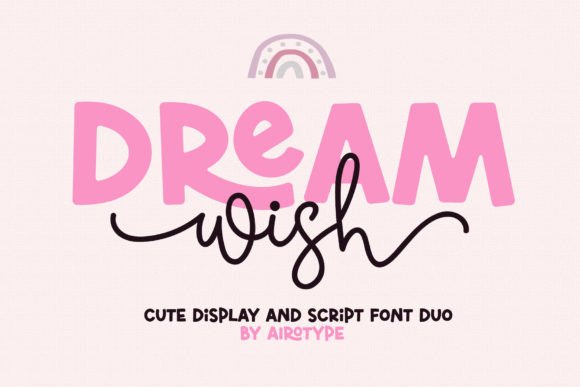
Dream Wish
إذا كنت تبحث عن أصول عالية الجودة مثل Dream Wish، فإن هذه الحزمة المميزة هي خيار رائع لمشاريعك الإبداعية.
سواء كنت تقوم بإنشاء منتجات الطباعة عند الطلب أو دعوات الزفاف أو رسومات وسائل التواصل الاجتماعي، فإن Dream Wish هو الخيار المثالي.